书法这个东西确实不好整,也可以说这个家伙很不好摆弄。往简单了说,在白色纸上写字就可以了,往深奥了说,那学问就大了去了,先不说别的,章法的布局就是书法创作中第一难把握的,如何布局,考量作者的技术含量、文化修养、灵性悟性,书法要有气、留住气。什么是气?气就是白,留气也就是留白。气是无颜色的,一笔下去,着墨的地方是黑色的,没着墨的地方就是白色的,白的地方就是气。
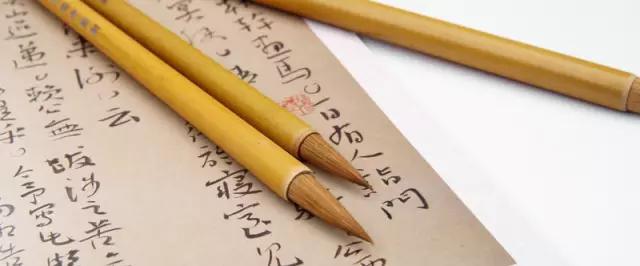
一般来讲,一个千古的要留传名的书家,有两点是必备的,其一自身意识即作品中含有的天地正气,合天地本性才与天地长存。其二有千古不尽之能量源,有能量的作品才能长久存活,长久存活才有历史的生命力,千人观万人仰,每次都要提取不同能量,必应有和天地相谐之能量玄机,同样一个蕴天地正气感灵天地之能的书家必现天地正德正形,书之体正笔健,赏心悦目是可想而知的。故而书家修艺修德,修心修性其至关重要是为天地人书自身的法则。
书法创作留白留气,就是把客观大自然空间应有的比例位置留出来,山川大地,万象都有走向走势,脉络沟梁,气流气路等合理的自然空间位,山川无来气之路为死地,在勘舆学的阴阳风水中也持别重要。阴阳家称无气之地为死宅,书家称无气之笔为死笔,无气之字为死字,无气之作为死作。
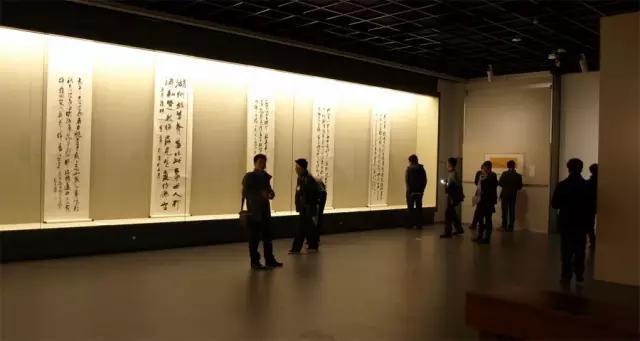
留气布白要依据书家行笔的粗细,字的力度占位量势,书家思想和内容。原则总之让人感到书作分量够,空间灵气神彩外发,舒畅大气,大气的字面就是气白要好,是多不是少,是大不是小。空灵就是气白空间充足,内含奇巧就显得灵动鲜活,有无限的想象生发的万字空间。空间严重不足的作品,则暮气沉沉,拥挤不堪,互相侵害,就象过密的山林在挣抢生存的阳光,有些叶木巳奄奄一息。使人感觉蔽气沉闷一片死气,严重者为死作。
书作也要防止气白过大,目中景物稀稀疏疏,一片萧条,大片空白则为衰作,气多也会变衰气。在视觉心里则为无力接通气流,山川之气是需要接通分流再梳配万物的。不能接通梳流则气散气消,气散气消则万物失生存,书作无生机。